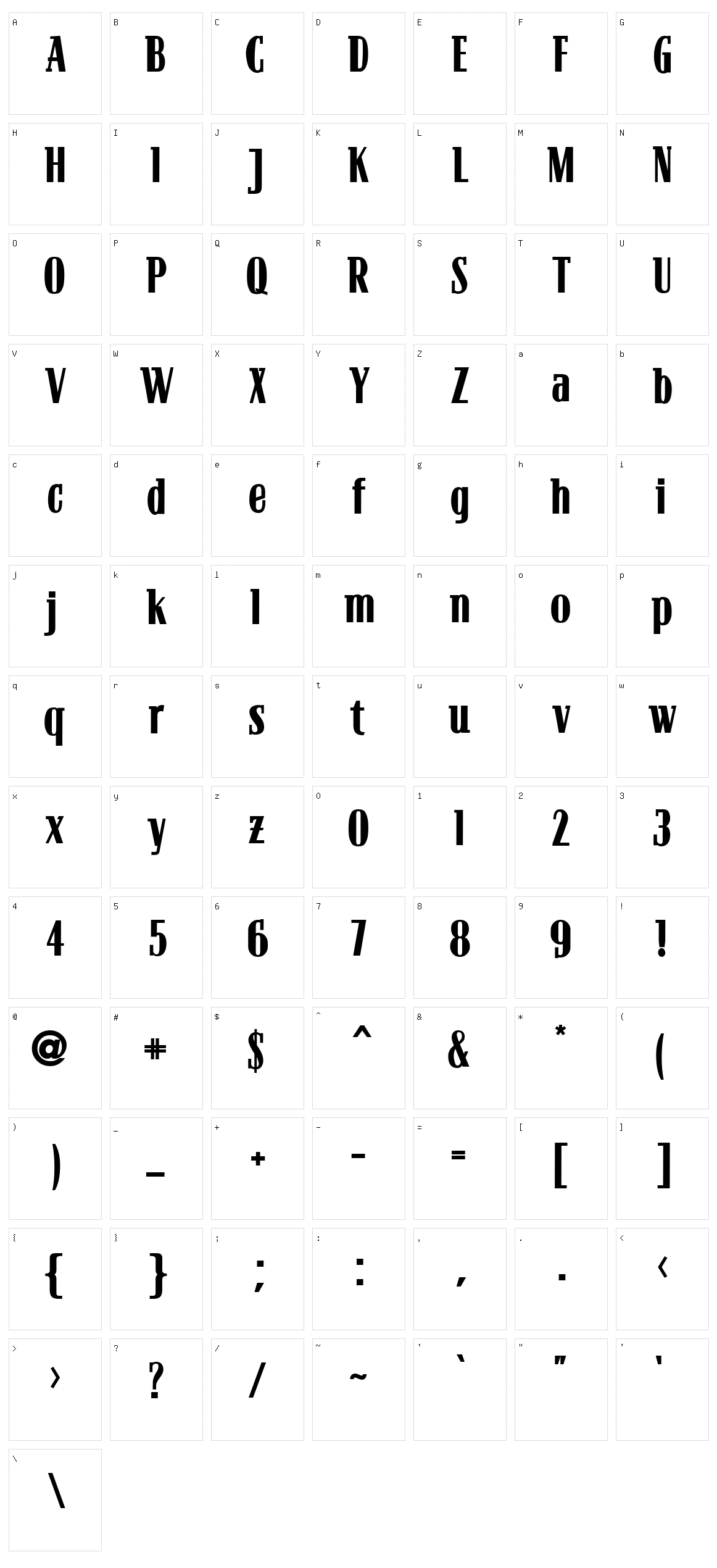
Bloc
Designed by: J?rgen Geiger
Category: Serif
Diese Schriften sind im Gegensatz zu
den "bekannten" voellig neu. Erst im Jahre 2000 gezeichnet,
haben sie natuerlich alle schon das Eurosymbol.